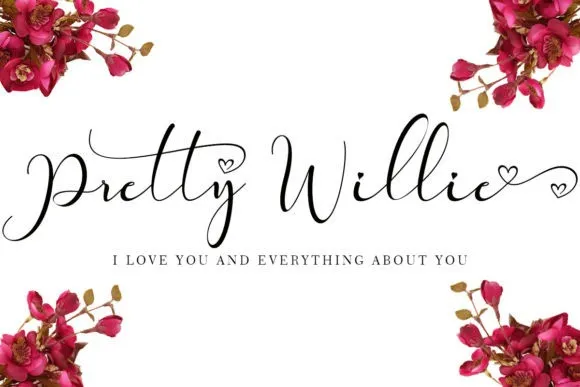
A fonte ‘Pretty Willie Calligraphy Font’ é uma herança do autêntico traçado a mão, que traz linhas curvas suaves e belas para enriquecer qualquer projeto. Este elegante estilo moderno vem diretamente da designer yogaletter6 de 99designs, criado em um ambiente acolhedor, repleto de suporte amoroso e compreensão, a par com sua esposa querida. Perfeita tanto para trabalhos profissionais quanto para desfiles pessoais, essa fonte oferece uma graça inimitável que torna seu trabalho ainda mais especial. Perfect for adding a touch of elegance and romance to your designs, this modern calligraphy font is ideal for anyone looking to elevate their creative projects with the beauty of handwriting.